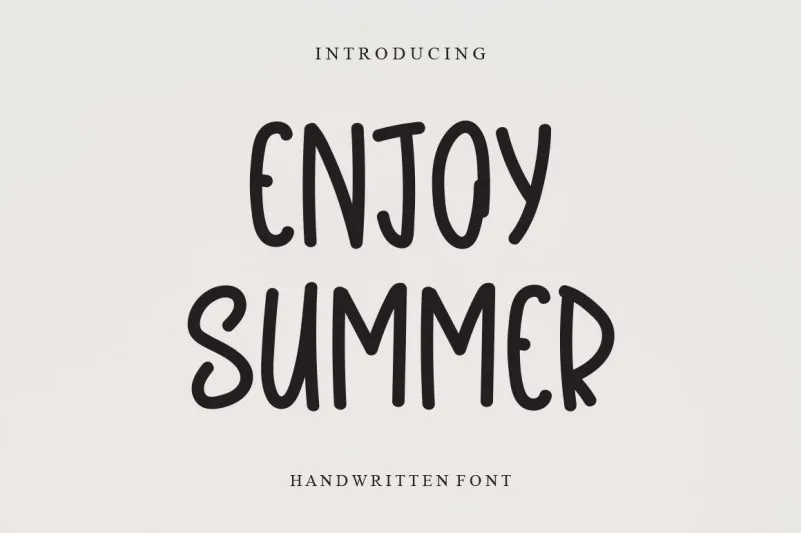
A fonte ‘Enjoy Summer Font’ é uma opção ideal para quem procura uma sugestão divertida e amigável para criar seus projetos de arte. Seja você que está procurando um estilo retrô e despojado para o seu Instagram ou mesmo aquele script delicado para adicionar um toque personalizado à sua DIY, essa fonte transformará a sua ideia em algo tão especial quanto merecido – uma obra de arte. Composta por uma escrita manual única, esta fonte cativante e simpática será a pedida certa para quem busca diversão no seu trabalho de design. Escolha a fonte ‘Enjoy Summer Font’ para trazer um toque descontraído e colorido ao seu próximo projeto gráfico.